25+ Font Groovy Terbaik untuk Sentuhan Tahun 60an
Benamkan diri Anda dalam energi psikedelik yang dinamis dari tahun enam puluhan dengan koleksi font asyik pilihan kami! Kompilasi eksklusif ini sangat cocok bagi siapa saja yang ingin memberikan sentuhan pesona vintage ke dalam proyek kreatif, besar atau kecil.
Berfokus pada perwujudan semangat era asyik, pilihan font kami mencakup sektor gratis dan berbayar. Apakah Anda mencari kebangkitan retro atau sekadar menyukai suasana hippie, daftar kami menjanjikan serangkaian pilihan yang akan membawa Anda kembali ke masa lalu dengan gaya dan estetika tahun 60-an yang rumit.
Memenuhi berbagai kebutuhan, kurasi kami melihat font dikembangkan dengan perhatian terhadap detail dan apresiasi mendalam terhadap estetika khas periode tersebut.
Selami dan jelajahi tipografi menawan ini yang tidak diragukan lagi akan memberikan kesan nostalgia pada karya Anda, menambahkan sentuhan klasik tahun 60an yang pasti akan meninggalkan kesan abadi.
Font Retro Pantai Groovy
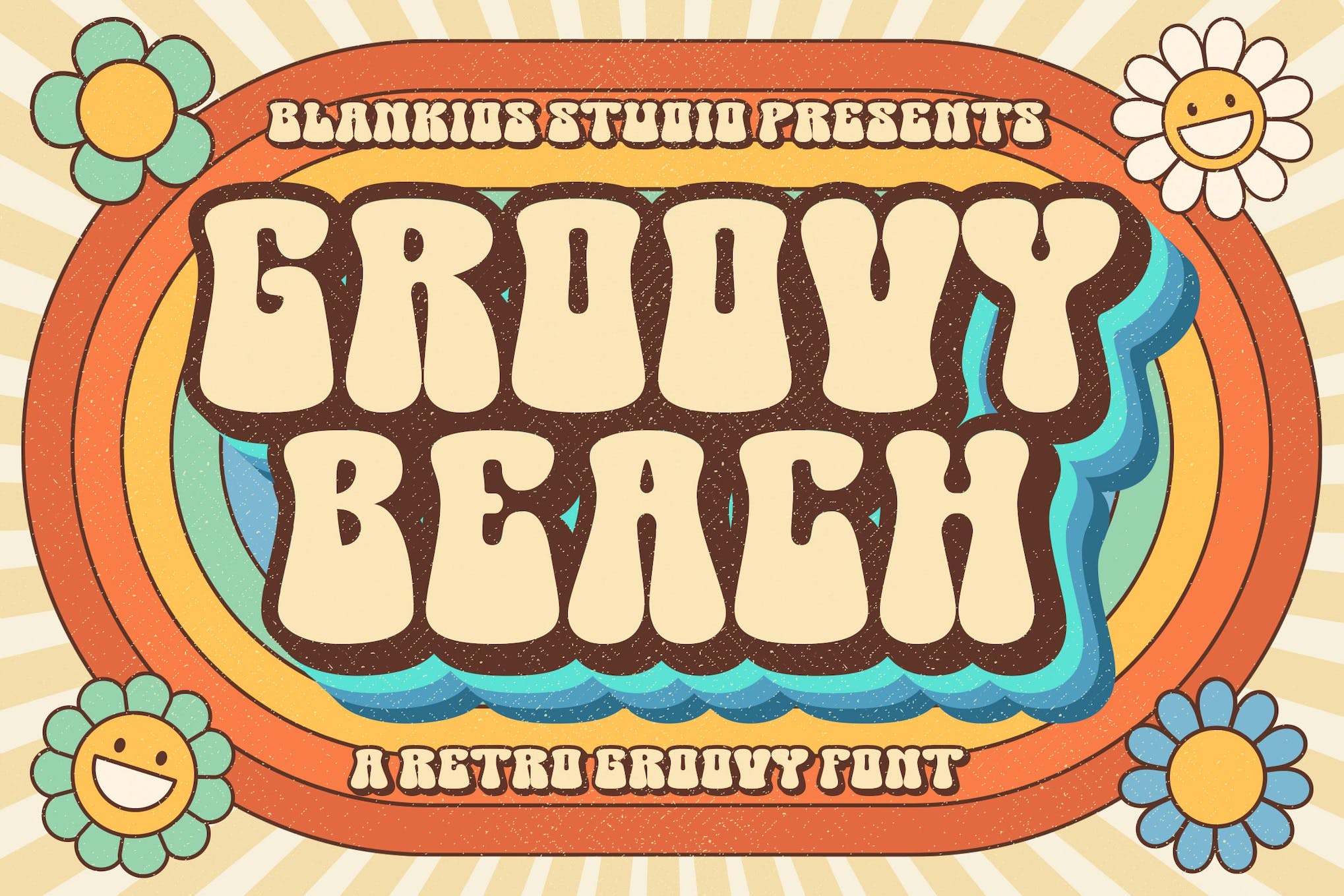
Groovy Beach Retro Font adalah aset multibahasa yang ideal untuk menciptakan desain yang berani dan menyenangkan. Terinspirasi dari tipografi vintage, font ini sangat cocok untuk berbagai kegunaan seperti sampul buku, poster, logo, dan merchandise. Dengan pemahaman estetika yang kuat, ia menyediakan huruf besar, huruf kecil, angka, tanda baca, dan menyertakan enkode PUA dan dukungan multibahasa, menjadikannya alat serbaguna dan mudah beradaptasi dalam perangkat desain apa pun.
Retro Oranye yang asyik
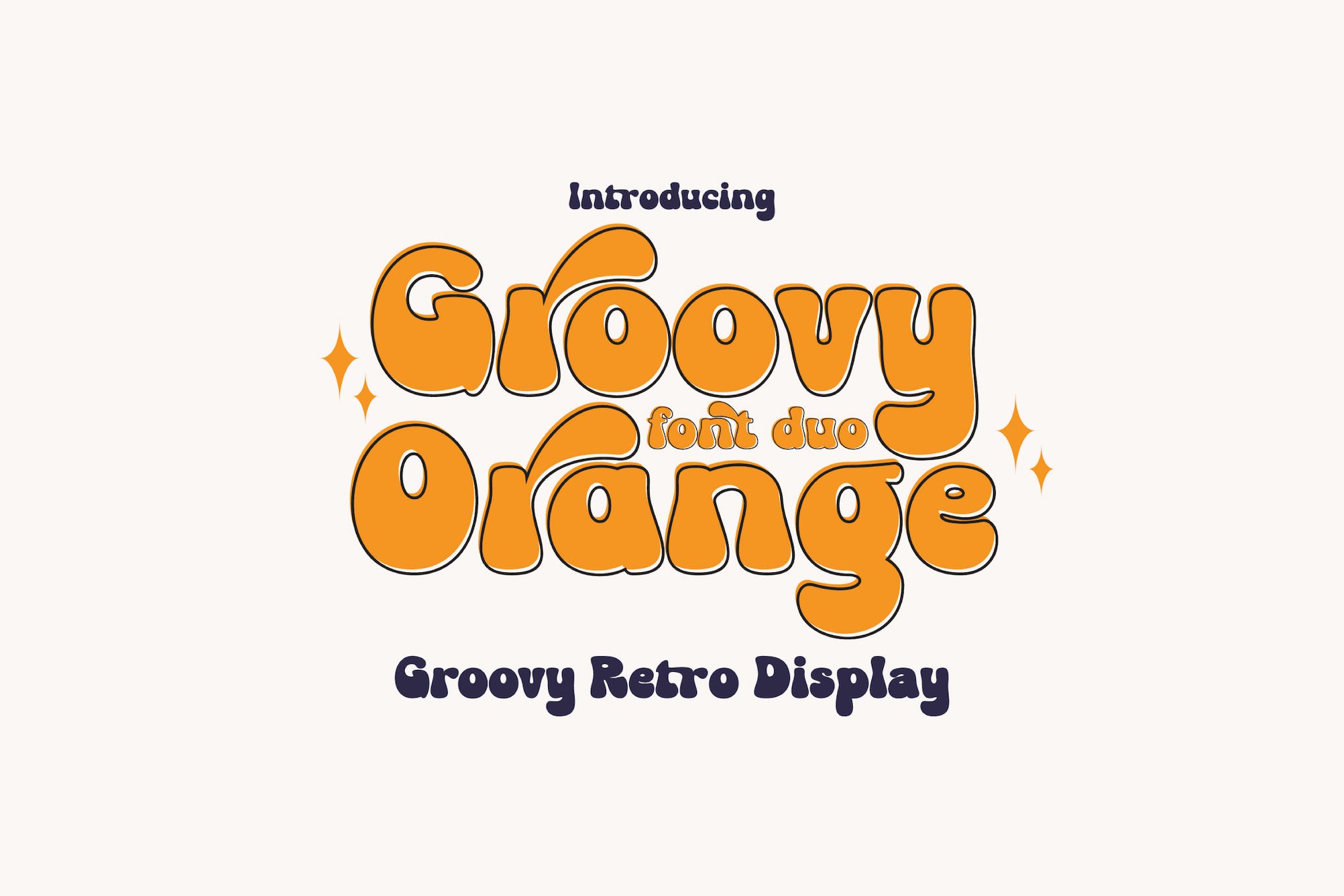
Aset Groovy Orange Retro adalah font tampilan yang dibuat dengan indah yang menawarkan suasana nostalgia yang menyenangkan dan estetika vintage yang menakjubkan. Bentuk hurufnya yang unik bekerja dengan lancar di PC & Mac dalam program populer seperti Adobe Illustrator dan Microsoft Word tanpa memerlukan perangkat lunak tambahan. Sempurna untuk menyempurnakan desain Anda, font yang mudah dipasang ini pasti akan menjadi tambahan favorit untuk koleksi font Anda.
Tulisan Tangan Asyik Hati Childkiss
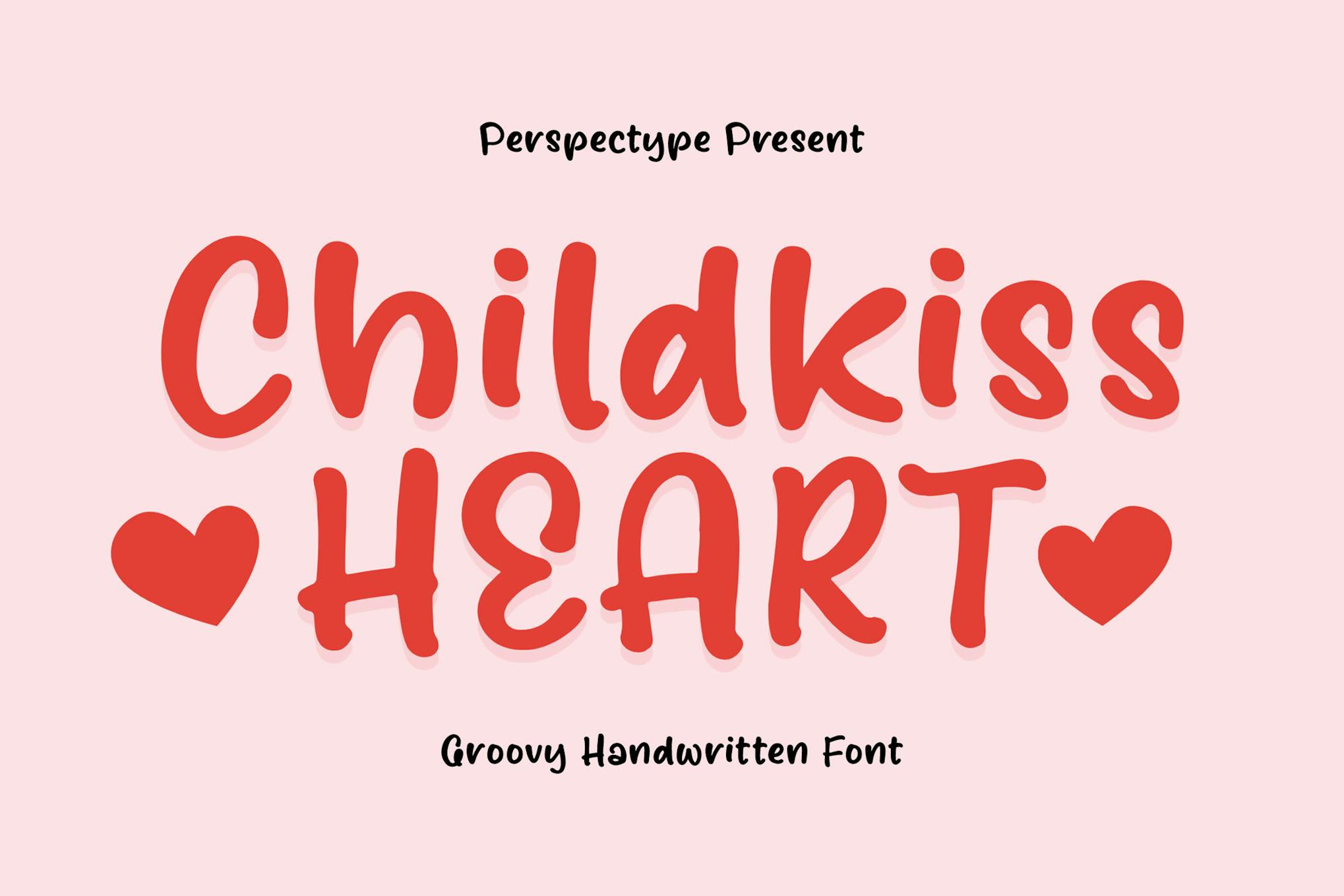
Jelajahi pesona ceria font Tulisan Tangan Childkiss Heart Groovy, cocok untuk menambahkan sentuhan pribadi pada proyek digital atau cetak Anda. Gayanya yang santai dan digambar tangan sangat bagus untuk segala hal mulai dari postingan media sosial hingga branding. Font tersebut mencakup file OTF, WOFF, dan TTF, memastikan fleksibilitas dan kenyamanan dalam proses kreatif Anda.
Jenis Huruf Kuning yang Menarik
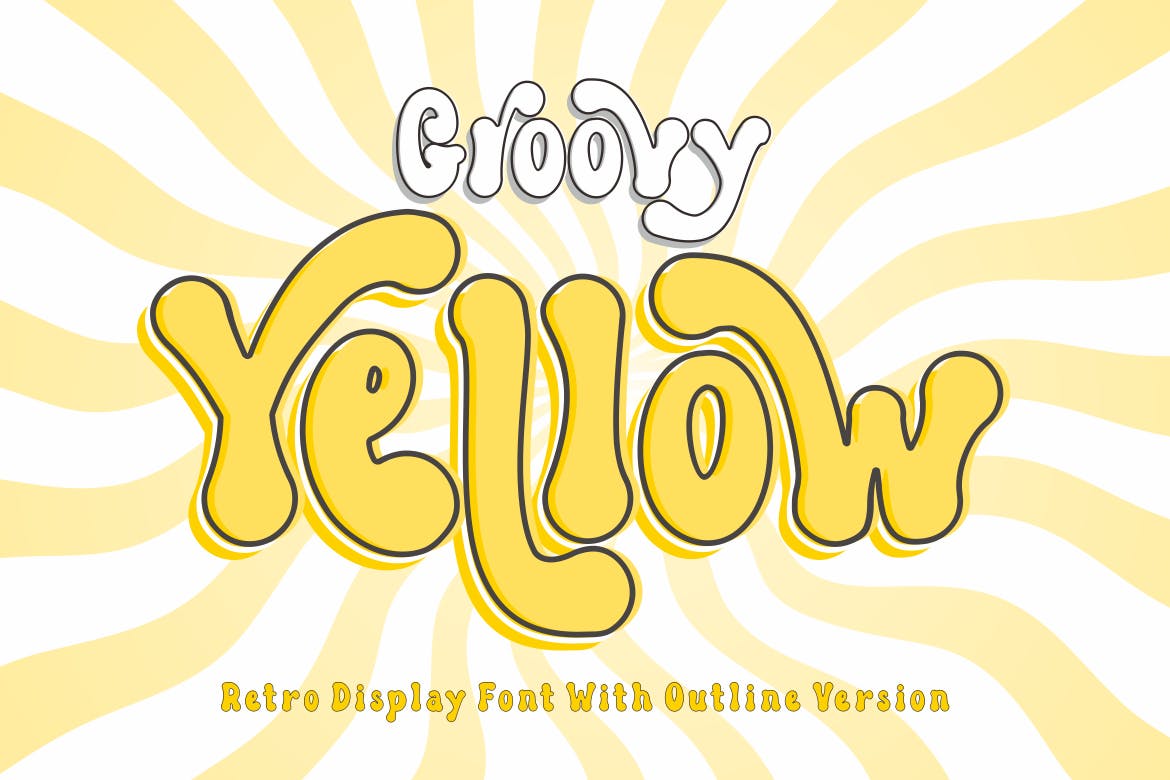
Groovy Yellow Typeface adalah font dinamis terinspirasi retro yang sempurna untuk berbagai proyek desain termasuk postingan media sosial, kutipan, spanduk situs web, dan banyak lagi. Estetikanya yang berbeda melengkapi mesin terbang huruf besar dan kecil bersama dengan angka, simbol, dan tanda baca. Plus, ia menyediakan dukungan multibahasa dan versi yang diuraikan. Tersedia untuk diunduh dalam format OTF, TTF, dan kedua WOFF, Groovy Yellow Font akan menambahkan sentuhan keren pada karya Anda.
Font Malam Asyik
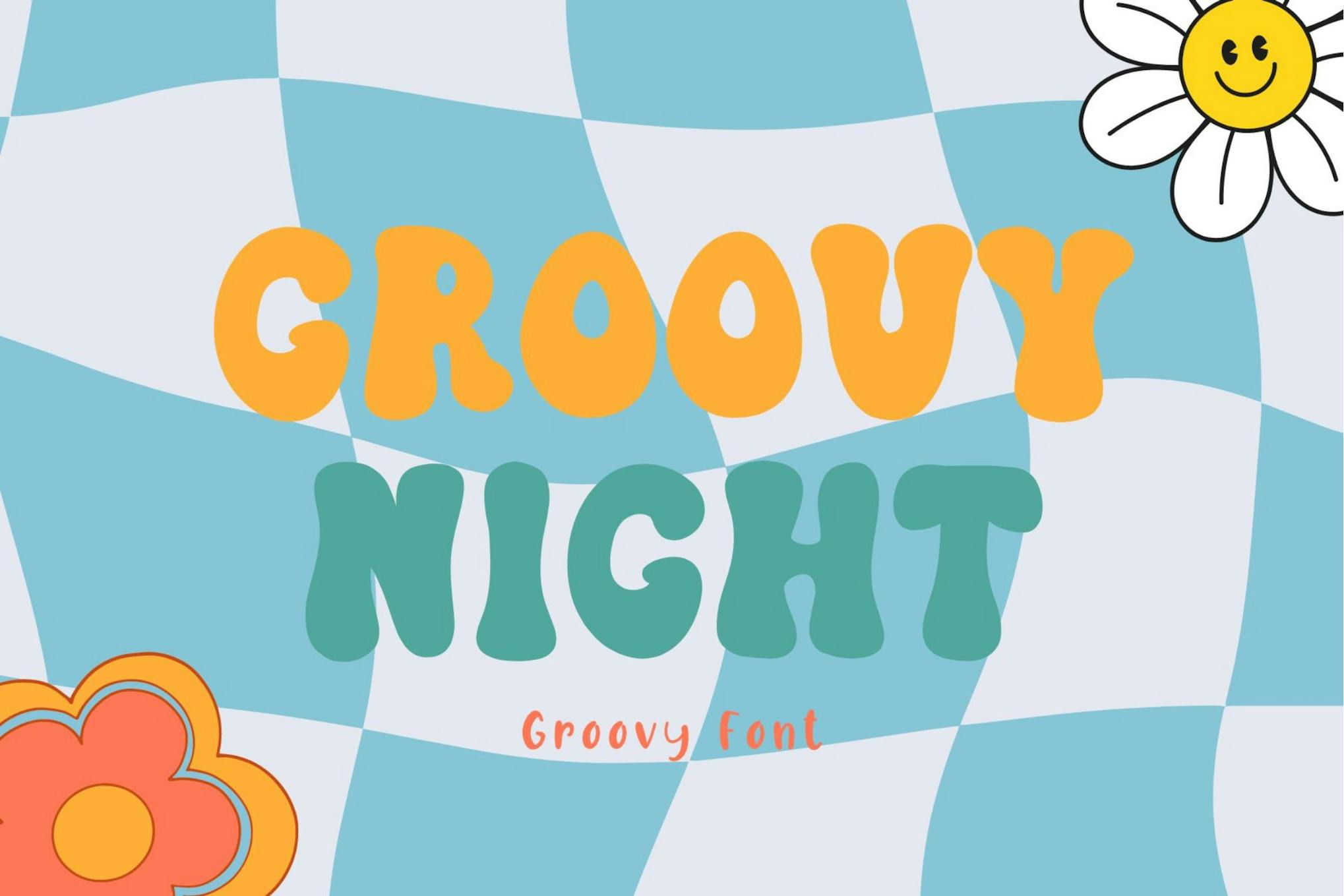
Groovy Night Font adalah font tampilan bergaya retro horor dengan struktur mirip tulang yang menetes seolah-olah berdarah. Sempurna untuk acara Halloween, ini menambah suasana dingin pada undangan, kartu pos, poster, dan judul Anda. Disediakan sebagai file OTF dan TTF, file ini mudah beradaptasi dengan berbagai aplikasi, memastikan daya tarik yang sangat menarik.
Jenis Huruf Groovy Grody
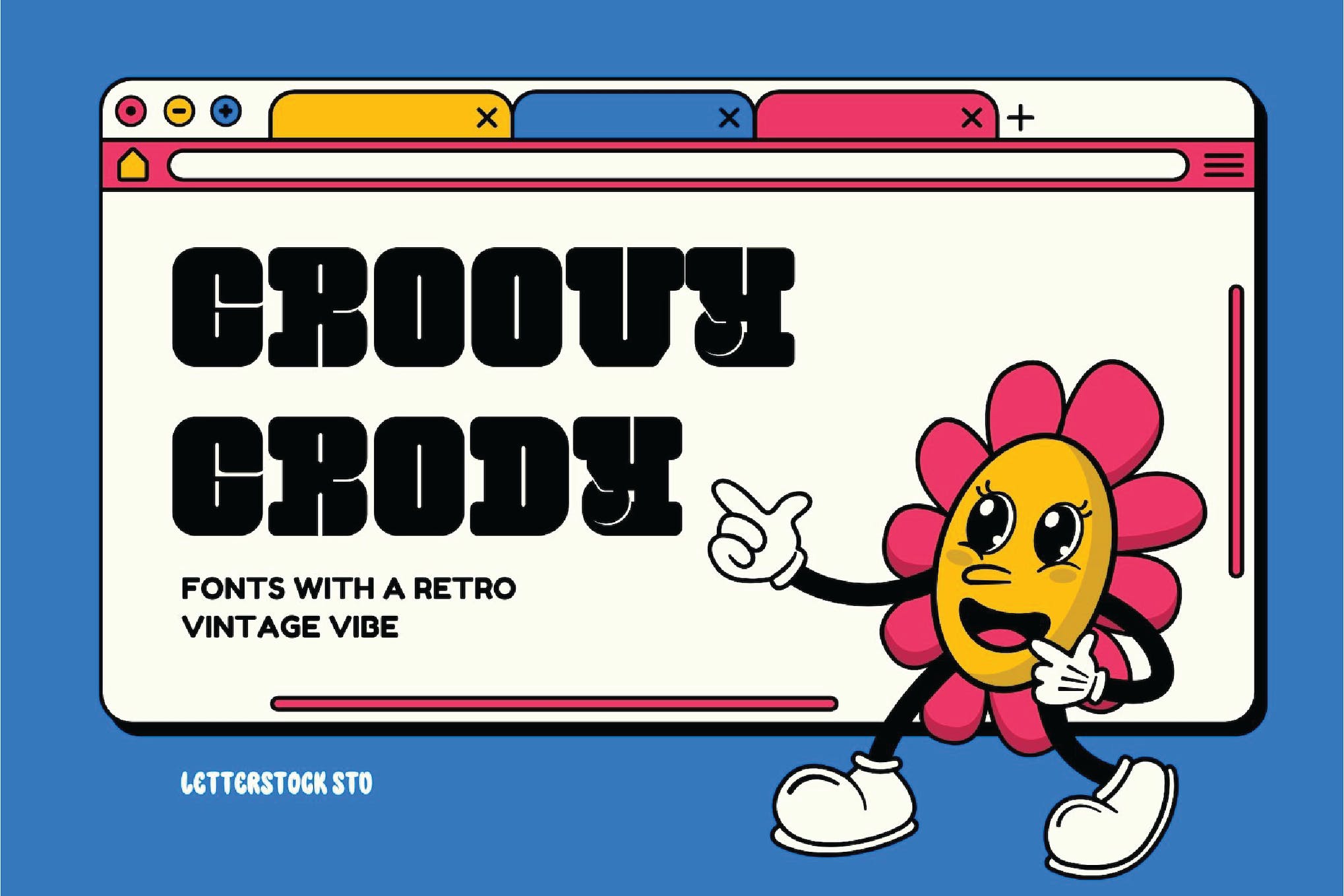
Lakukan perjalanan ke masa lalu dengan jenis huruf “Groovy Grody”. Didesain dengan huruf serif tebal dan tebal, font ini memancarkan daya tarik vintage dan sangat cocok bagi mereka yang ingin menambahkan sentuhan nostalgia pada proyek mereka. Baik itu membuat poster retro yang menghipnotis, mendesain spanduk tebal, atau membuat logo unik, “Groovy Grody” menyediakan kanvas ideal untuk kreativitas vintage.
Font Retro Asyik
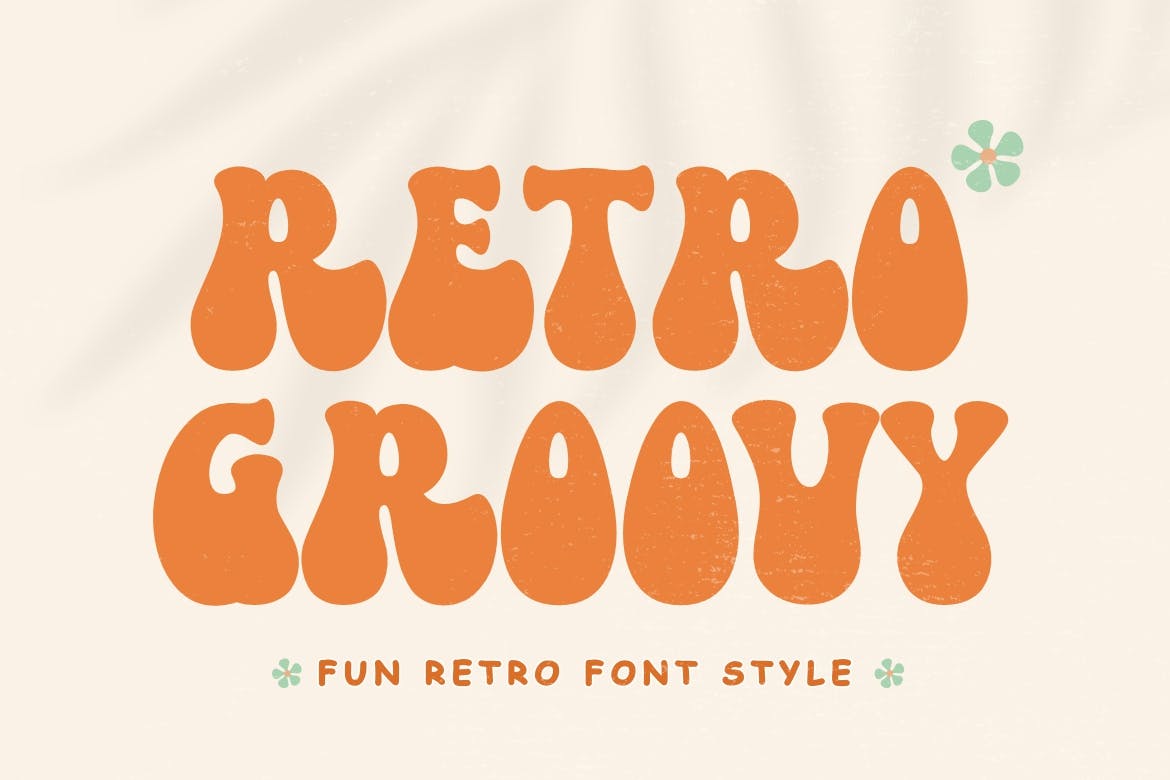
Retro Groovy Font adalah font yang sangat berani dengan estetika retro yang menyenangkan namun modern. Menampilkan karakter huruf besar dan kecil, angka, tanda baca, dan dukungan bahasa yang ekstensif, gaya ini memancarkan daya tarik gaya lama yang gemuk dengan karakter yang digariskan. Sangat cocok untuk branding, mendesain kemasan, membuat template cetak cerdas, atau bahkan proyek mode, Retro Groovy Font adalah tambahan serbaguna untuk hampir semua proyek kreatif.
Jenis Huruf Teman yang Menyenangkan
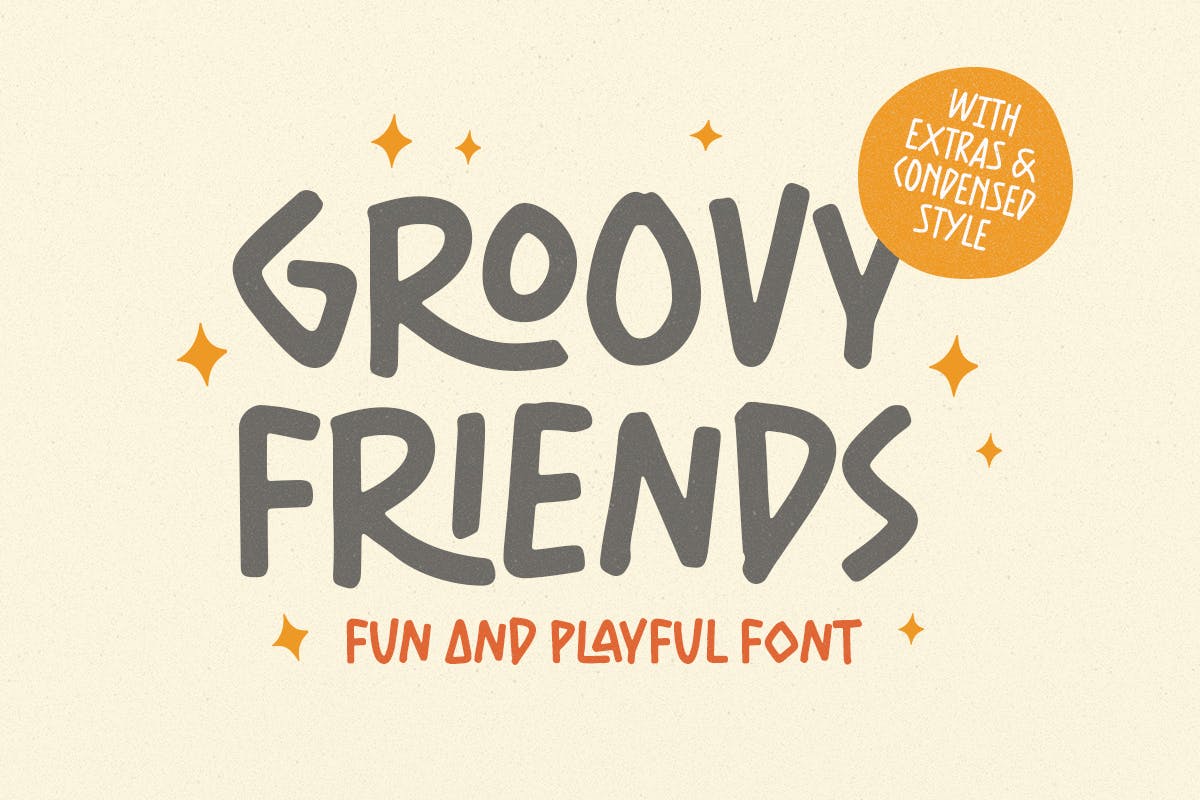
Groovy Friends Typeface adalah font lucu dan menyenangkan yang dapat digunakan untuk berbagai tujuan, mulai dari buku cerita anak-anak hingga desain kemasan. Tersedia dalam dua versi, satu dengan doodle dingbats sebagai tambahan, ia juga menawarkan versi solid dan SVG dengan berbagai fitur termasuk angka dan tanda baca, dukungan multibahasa, ligatur, dan pengkodean PUA. Paling baik digunakan dalam program desain yang mendukung fitur OpenType dan panel Glyphs.
Tampilan Sindrom Groovy
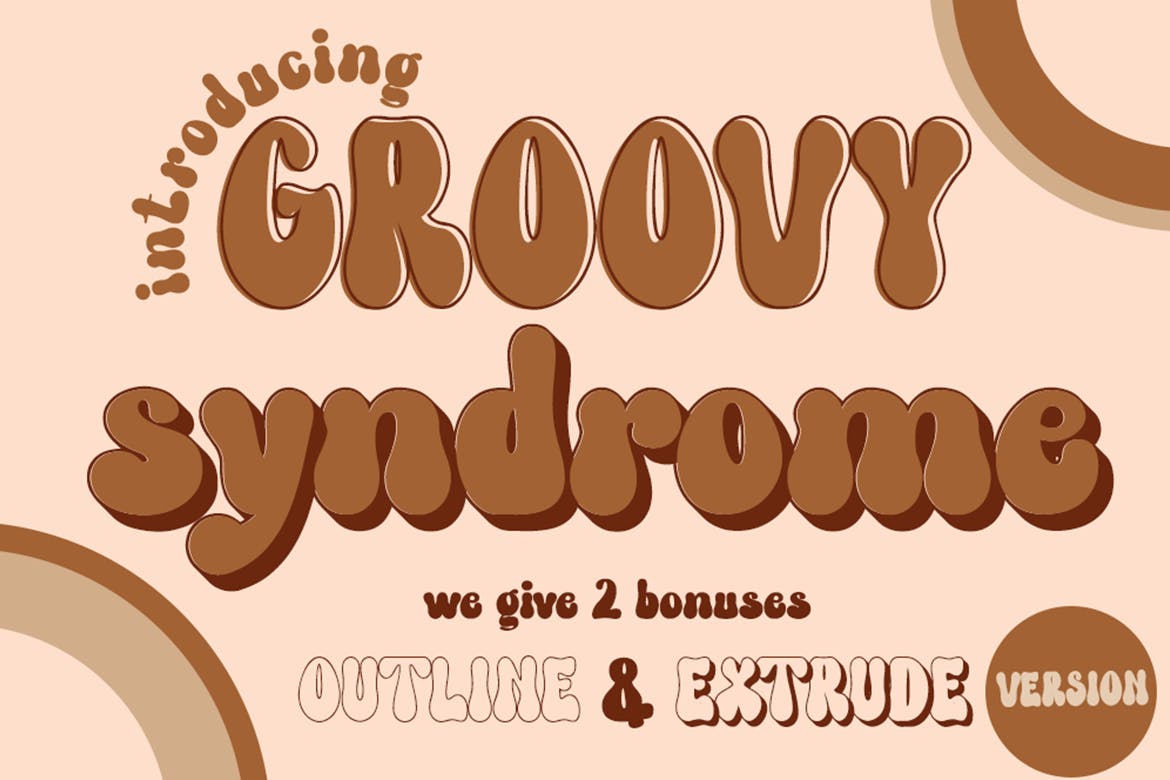
Groovy Syndrome Display adalah font bergelembung yang digambar tangan dan menampilkan tampilan retro yang keren. Paket ini hadir dengan tiga font bergaya: Regular, Outline, dan Extrude; serbaguna untuk membuat kutipan dan kata-kata retro. Ideal untuk berbagai media seperti prokreasi, kemeja, stiker, logo, branding, kartu ucapan, majalah, media sosial, dan banyak lagi. Dikirim dalam file ZIP dengan file font OTF dan TTF.
Font Groovy Pencinta Makanan Retro
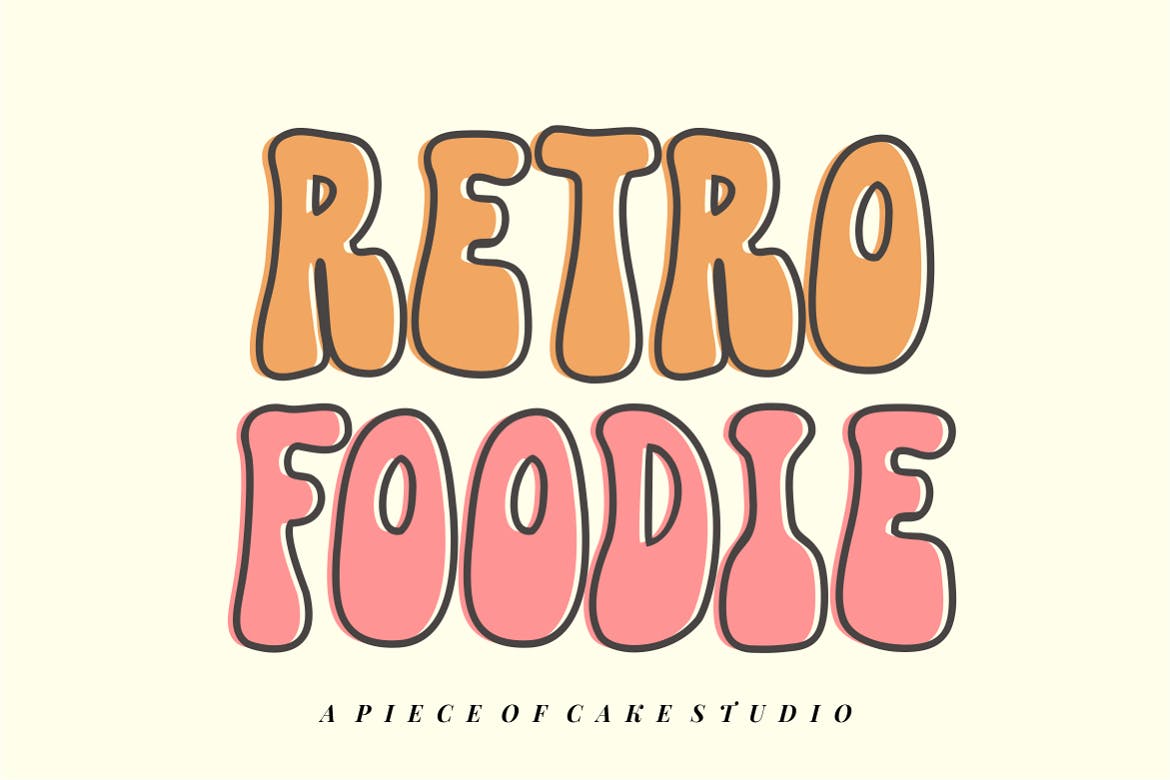
Retro Foodie Groovy Font, jenis huruf tampilan dinamis, sangat cocok untuk berbagai konteks desain seperti tema retro, postingan media sosial, tagline, dan spanduk situs web. Ini mencakup perpaduan huruf besar dan kecil, angka, simbol, dan tanda baca serta dukungan multibahasa. Versi garis besar tersedia untuk diunduh dalam format tipe terbuka yang mudah diakses (.otf). Nikmati penggunaan font serbaguna ini untuk proyek kreatif Anda!